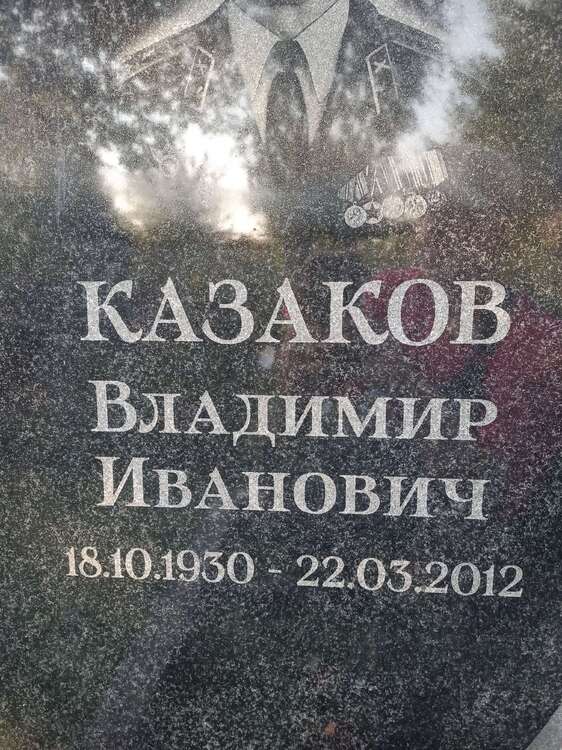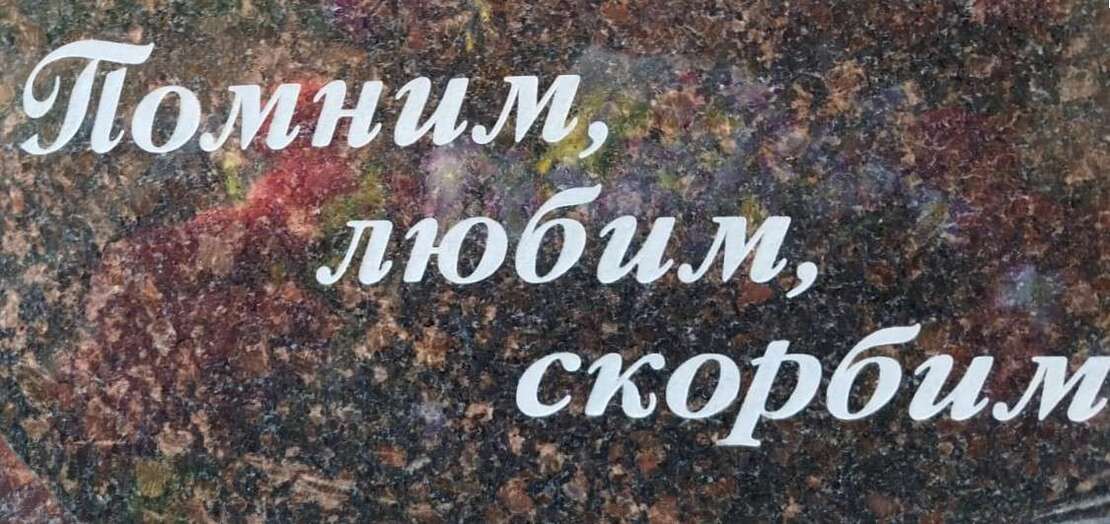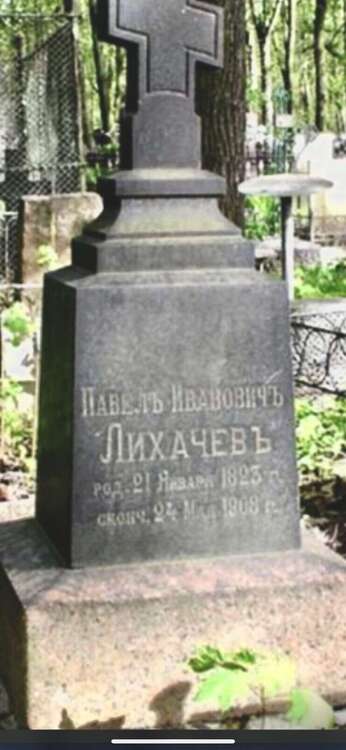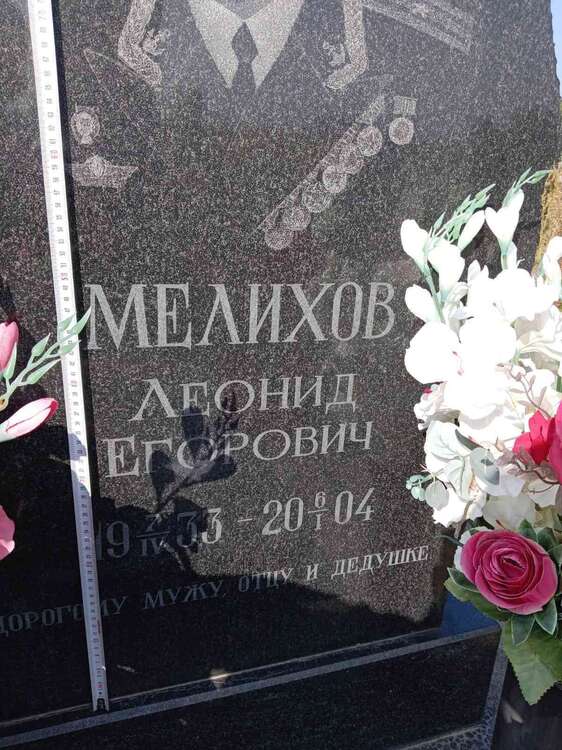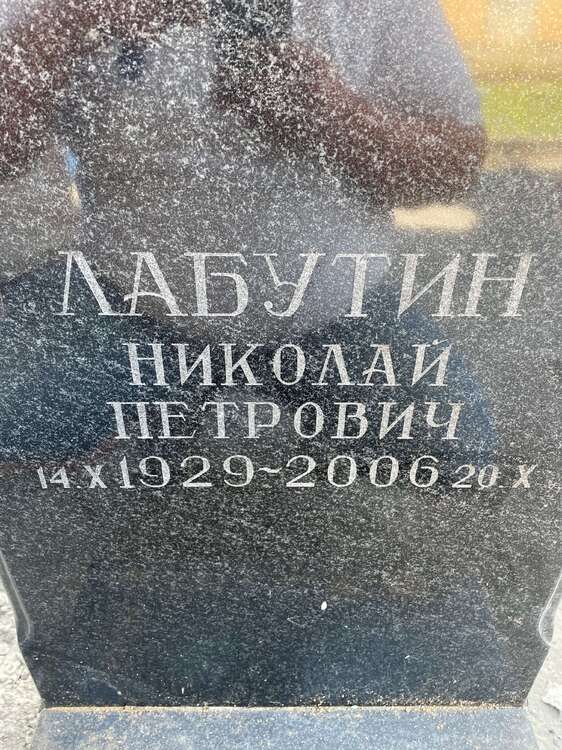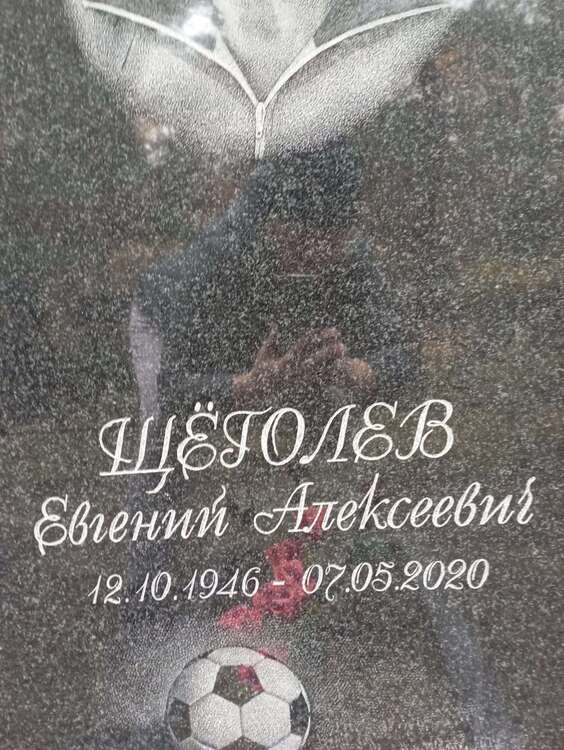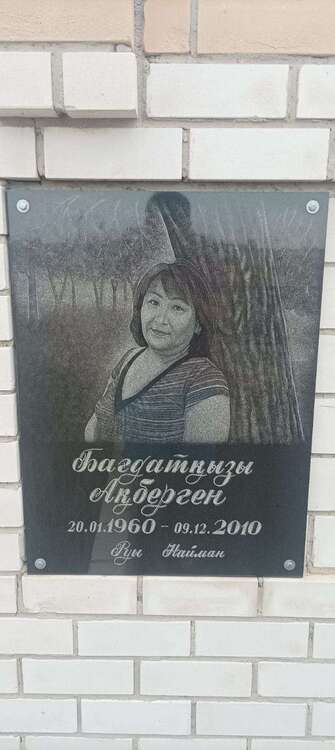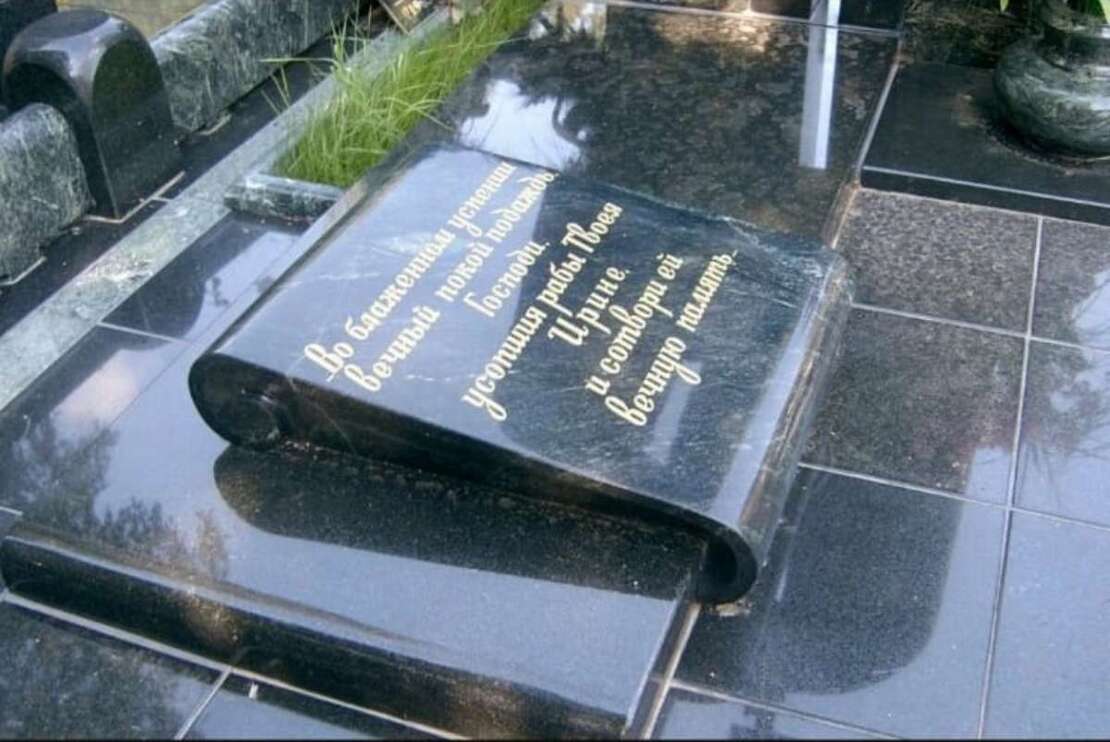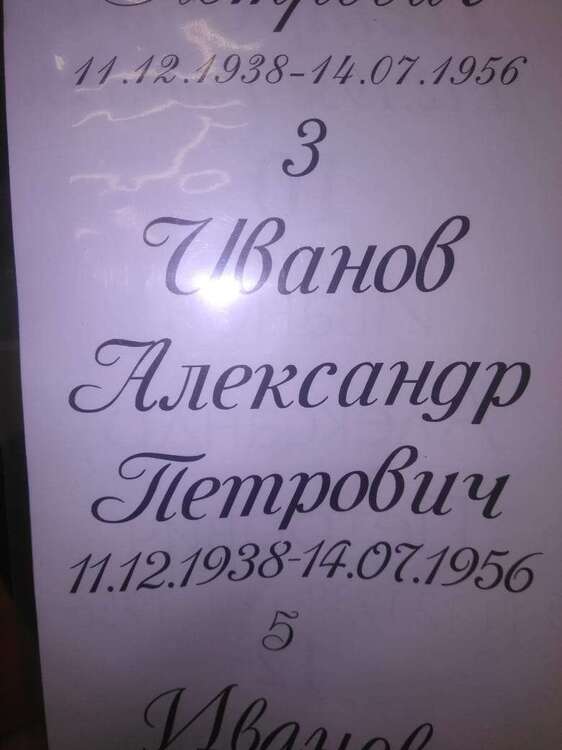
Здравствуйте, коллеги! Пожалуйста, помогите найти данные шрифты:
Помогите найти шрифт, пожалуйста.
Хренотень полнейшая. Симбеоз из чего попало. Я даже, когда рубил вручную, такой хренотенью не занимался.
@Alexsey Это ручник. Ищите похожий, или отрисовывайте и монтируйте
Добрый вечер! Может, кто знает такой или похожий
@Gizmo Попробуйте этот. Может подойдет
Measure
Proletariat
Спасибо, Алена! Measure практически один-в-один
Доброго времени суток всем. Работал станок, времени искать шрифт не. хватает. Подскажите его имя, кто знает. Спасибо заранее.
@a-revus Самое похожее - Naga Regula / AcademyCTT Bold
Ну, а цифры дат  придется подбирать из других шрифтов.
Очень срочный заказ. Плиты рядом, нужна идентичность. Помогите, пожалуйста, найти шрифт.
@ptizzza Это ручник. Похожий может и можно найти.....Но в образце есть элементы, которых явно не подобрать. И даты придется подбирать отдельно.
@алена Понятное дело, что ручник. Но основу он с какого-то копперплейта брал. Сейчас скинули более качественное фото. Уверена, была распечатка.
@ptizzza Ни факт. Наш просто берет и рубит...... Надо перелопатить все доступные ресурсы.......В моем "чемоданчике" такого нет.
@ptizzza Не было никакой распечатки. Расчерчивалось белым карандашом направляющие и машинкой гравировалось. На глаз, от руки. То же самое нужно делать и на второй плитке. Чтобы сделать аналог шрифта, готовьтесь заплатить от 2500р за приближённую имитацию. Нет - подбирайте подходящий курсив.
То же самое нужно делать и на второй плитке
Можно помучиться по правильной фотке в центр надписи и с минимумом искажений отрисовать шрифт в векторах, недостающие знаки составить из элементов имеющихся или дорисовать вручную.
Проще скопировать шриховкой на лист, копирка штриховки по разметке, дорисовать вручную и настучать машинкой:dontknow:
@zelenok Это-то я всё умею, а вот когда выкладывают такие фотографии, с просьбой помочь, понимаешь, что человек ничего из вышеперечисленного не может. Поэтому в данном случае либо заплатить, либо не заморачиваться и сделать более-менее подходящий шрифт. Потому, как оригинал доброго слова не стоит.
Здравствуйте, уважаемые! Помогите со шрифтом пжт:help: